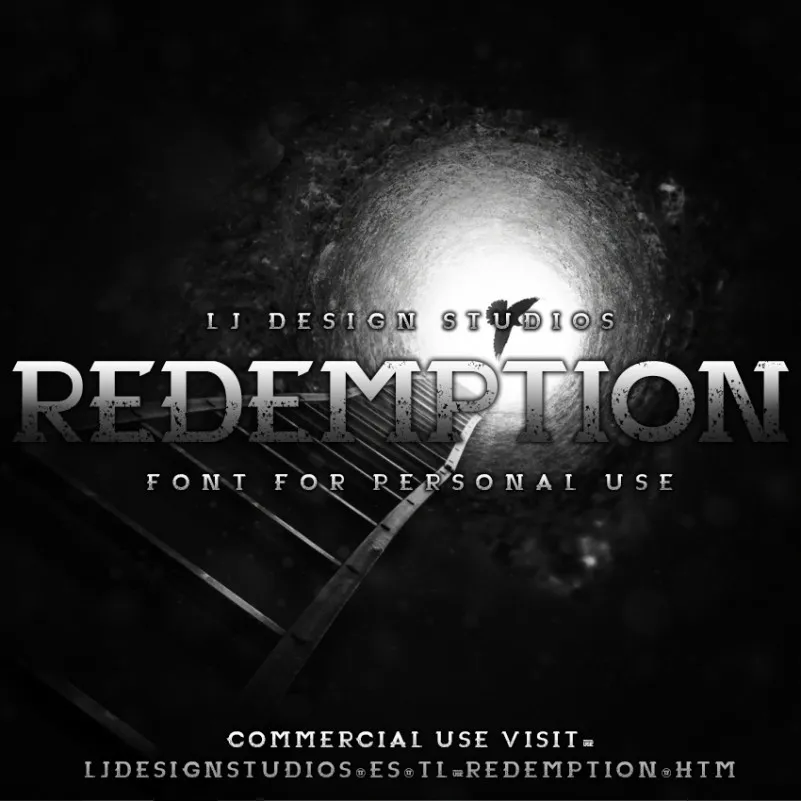
Redemption Font – Download Grátis
A fonte Redemption é uma deliciosa incursão no mundo da Blackletter Fonts, criada pelo designer Hamilton para aqueles que buscam algo único e poderoso. Com seus traços leves e elegantes, a Redemption captura uma atmosfera sombria e sofisticada, ideal tanto para uso editorial quanto comercial. Ideal para gráficos de arte que desejam um tom vintage sem ser antiquado, essa fonte oferece o equilíbrio perfeito entre controle e criatividade. Seja para títulos chamativos ou textos detalhados, Redemption não decepciona, garantindo uma experiência visual atraente. Esta é mais do que apenas uma fonte: é um ato de liberdade em linguagem. Visite o site da Hamilton Design Studio para explorar mais e experimentar a verdadeira magia de Redemption.